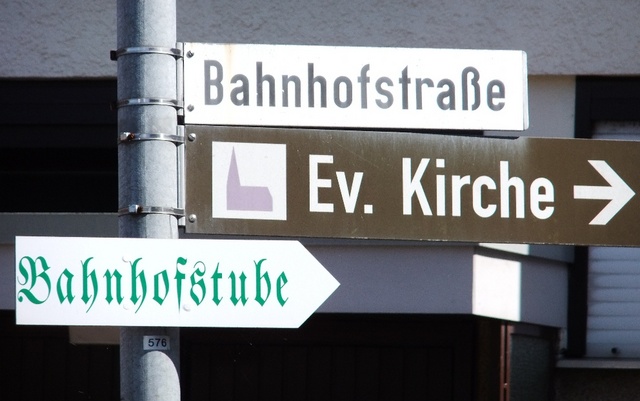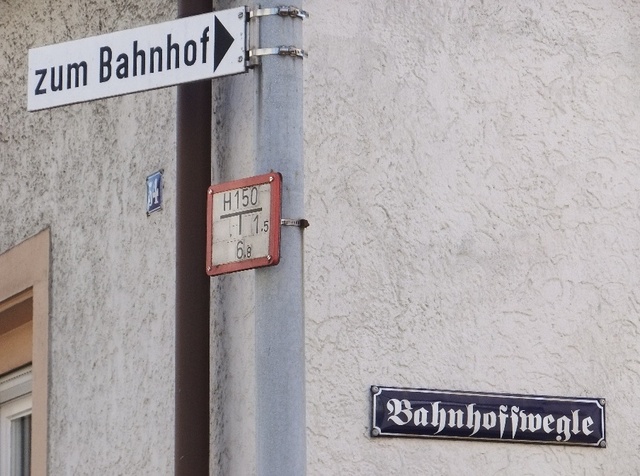
Neue Rechtschreibung?
ich kann auch keine Fraktur mehr lesen, nur wenn ich großen Hunger hab, schaff ichs grad noch
Gaststätte, Bier und Schweinshaxn zu entziffern.
:)
Gerade kommt mir eine Idee!
Ich werde mein Klingelſchild in Fraktur ausdrucken!
Denn die Jugend von heute ...
kann auch keine Fraktur mehr lesen,
... und somit werden ich vielleicht künftig davor verschont, dass diese Jugend, wenn sie auf dem Weg von oder zu ...
Gaststätte, Bier und Schweinshaxn
.. irrtümlich nachts bei mir klingelt ;-)
(Das ist der einzige Haken an der zentralen Wohnlage direkt neben der Post *seufz* Galerie, aber zum Glück bin ich ja eh Nachtmensch, die Pubertierenden reißen mich daher selten aus dem Schlaf ...)
Ich las einen Text, in dem das Wort Türkischrot vorkam, und ich brauchte mehrere Anläufe, um es zu verstehen.
super, endlich mal ein neues beispiel anstatt der wachstube. :peng:
ehrlich... ich habe auch zwei anläufe gebraucht, der zweite versuch das wort zu entschlüsseln hatte aber schon das richtige ergebniss türkisch-rot hervorgebracht. alleinstehend ohne context ist das natürlich komplizierter zu entschlüsseln, ich gehe aber mal davon aus es stand innerhalb eines satzes. magst du uns nicht mal den kompletten satz/quelle/zitat hier zeigen? ich würde mal behaupten mit dem entsprechendem context hätte kaum jemand an tür-kirschrot, türkis-rot oder türkenschrot gedacht.
Vers-Endung/Ver(-)sendung wird auch gern genommen. Nicht dass jemand behauptet, ich würde Gegenargumente unterdrücken. ;-)
Ich kann auf diese Beispiele aber immer nur erwidern, dass sie eine generelle Eigenschaft der deutschen Sprache sind und auch mit einem langen s nicht gelöst wären. Man denke an die bekannten Blumento-Pferde. Solange nicht ein Sprachwissenschaftler statistisch belegt, dass die Morphemgrenzen-Fehlerkennungen signifikant öfter bei Nahtstellen mit einem s auftauchen, trägt dies Pro-lang-s-Argument für mich nicht.
Hach, das bringt ja meine Kindheit zurück!
Morgenstern
Abendstern
Zwergelstern
:-P
Solange nicht ein Sprachwissenschaftler statistisch belegt, dass die Morphemgrenzen-Fehlerkennungen signifikant öfter bei Nahtstellen mit einem s auftauchen, trägt dies Pro-lang-s-Argument für mich nicht.
Stimme Dir da voll zu, eigentlich braucht es aber ja nicht mal das. Die Tatsache daß im Grunde alle angegebenen Beispiele bezüglich des modernen Sprachgebrauches Exoten sind (Wach-Stube? Mir war das Wort vor dieser Diskussion noch nie untergekommen. Und für ein Schwachsinn ist denn eine Wachs-Tube?) zeigt daß es im Prinzip keine Rolle spielt. Sonst wären da schon viel naheliegendere Beispiele aus dem täglichen Gebrauch angeführt worden. Ich kann mich im Moment wirklich nicht erinnern wann ich mich das letzte Mal beim konzentrierten Lesen »Verlesen« hätte. Aus dem Augenwinkel in der U-Bahn ist das noch mal wieder etwas anderes, da gehen dann aber auch ganz andere und grundlegendere Sachen bei der Erfassung schief, nicht nur Morphemgrenzen.
ich habe auch zwei anläufe gebraucht, der zweite versuch das wort zu entschlüsseln hatte aber schon das richtige ergebniss türkisch-rot hervorgebracht. alleinstehend ohne context ist das natürlich komplizierter zu entschlüsseln, ich gehe aber mal davon aus es stand innerhalb eines satzes. magst du uns nicht mal den kompletten satz/quelle/zitat hier zeigen? ich würde mal behaupten mit dem entsprechendem context hätte kaum jemand an tür-kirschrot, türkis-rot oder türkenschrot gedacht.
Ich finde den Satz nicht mehr. Es ging um Farben in einem Prospekt. Der Verleser Türkis ist in einem Text über Farben nicht abwegig. Türkisch-Rot war mir neu. Der Verleser Türkis-Rot hätte mit langem s nicht passieren können. Ebenso wie die Versendung in der Tat eindeutig ist mit langem s, wenn es sich um Post handelt. Ich fand meinen Verleser nur lustig, weil das so selten vorkommt, daß man drei Anläufe braucht. Und weil es in diese s-Diskussion paßt. Das lange s kommt aber nicht mehr in die Antiqua, auch wenn es hier und da nützlich zu sein scheint. Selbst wenn jemand auf die Schnapsidee kommt, das "wissenschaftlich" untersuchen zu wollen, kommt kein langes s mehr in die Antiqua.
Und für ein Schwachsinn ist denn eine Wachs-Tube?
Früher konnte man Wachs auch in Tuben kaufen, um dann Stoffe oder Leder zu imprägnieren. Wenn ich mich recht entsinne, gibt es heute noch Wachs für Barbour-Jacken in Tuben.
Edith vergaß: Warum schreibt man eigentlich überhaupt Wachs? Für den Laut haben wir doch das x?
Und die Wachstube, also die Wach-Stube, ist jedem Soldaten bekannt. Vielleicht nennt man sie heute anders, ich kenne jedenfalls die Wachstube aus meinem Militärdienst. In der Wachstube wurde möglicherweise auch mal ein Leder gewachst. Und anschließend ein Brief geschrieben ...
Man könnte ja jetzt sagen, die neue Rechtschreibung löst solche Probleme wie Türkischrot mittels optionalem Koppelstrich im Falle von möglichen Zweideutigkeiten ... selbes Problem, anderes Werkzeug (das aber auch bei anderen Stellen befriedigend funktioniert, nicht nur an den Wortfugen mit s).
Mir ist aber klar, dass in einem Werk über Farben zig verschiedene, gekoppelte Farbbezeichnungen vielleicht unpraktisch sind.
Ich werde mein Klingelſchild in Fraktur ausdrucken!
... und somit werden ich vielleicht künftig davor verschont, dass diese Jugend, wenn sie auf dem Weg von oder zu ...
Einspruch, euer Ehren. Die Kriterien des Anspruchs legt einzig der "Anspruchsteller" fest. Das kann der unbedarfte Leser sein, für den es gar keinen Zweifel am k gibt, das kann aber auch der Typograf sein, der über das selbe k die Hände über dme Kopf zusammenschlägt. Es gibt nicht einen Qualitätsanspruch.